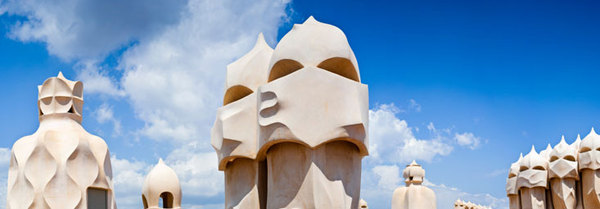
Vasava, uno de los estudios de comunicación mas relevantes del territorio español, a diseñado recientemente la tipografía personalizada que llevaran
las equiparaciones oficiales del FC Barcelona para la liga 2012-2013.
Según cuentan desde el estudio, esta tipografía esta basada en los cortes sutiles y ángulos de las chimeneas de los centinelas de la
Pedrera de Gaudí.